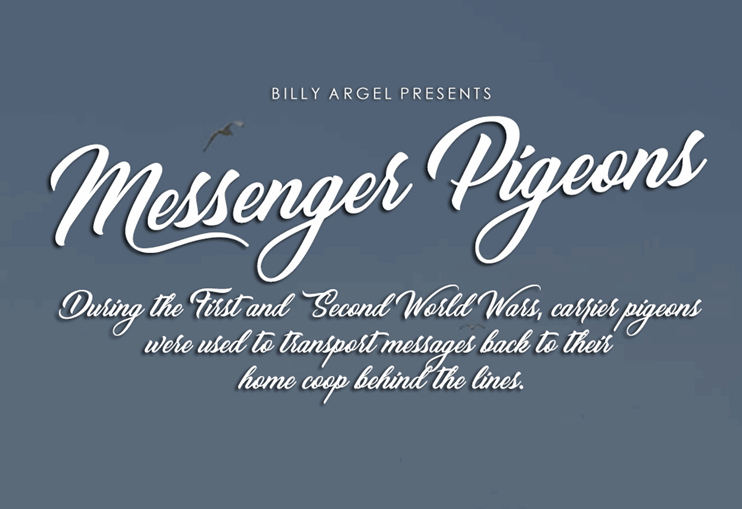
Messenger Pigeons Font – Download Grátis
A fonte ‘Messenger Pigeons’ é uma elegante fonte escrita à mão criada pelo designer Billy Argel. Ideal para aqueles que buscam personalidade e estilo ao criar seus projetos digitais, esta opção oferece um toque especial a qualquer texto. A versão completa da font inclui ligaturas otimizadas para melhor leitura e recursos de OpenType, como alternativas estilísticas que adicionam uma camada extra de personalização aos textos. Essa fonte é especialmente adequada para projetos pessoais ou até mesmo pequenos negócios. Ela também pode ser facilmente adaptada para uso comercial, graças ao envio da URL específica do designer pelo site. Para conhecer mais sobre outras criações e recursos de Billy Argel, visite www.billyargel.com ou http://www.facebook.com/billyargelfonts. Com a ‘Messenger Pigeons’ você pode adicionar um toque único e criativo aos seus designs digitais, seja para gráficos em preto e branco ou para textos coloridos. Uma fonte perfeita para qualquer projeto que deseje destacar-se com uma escrita autêntica e personalizada.